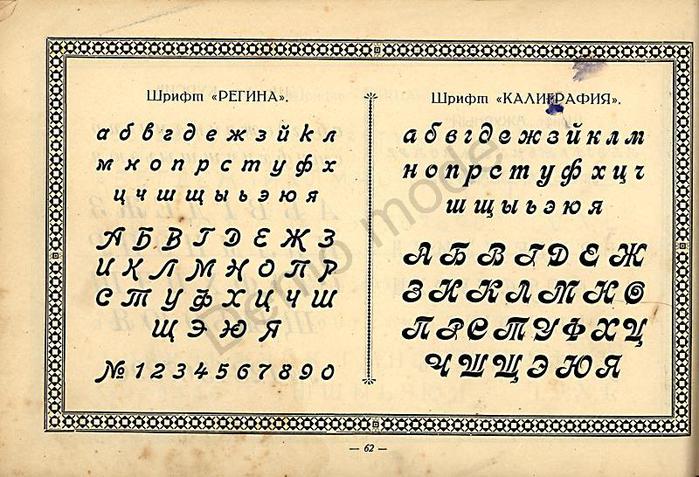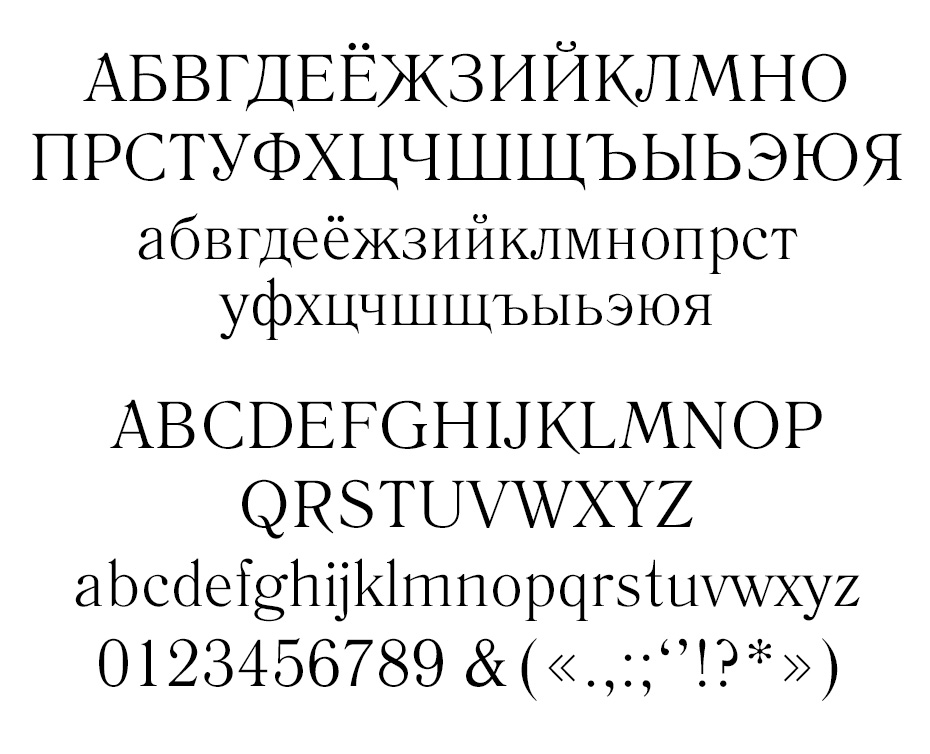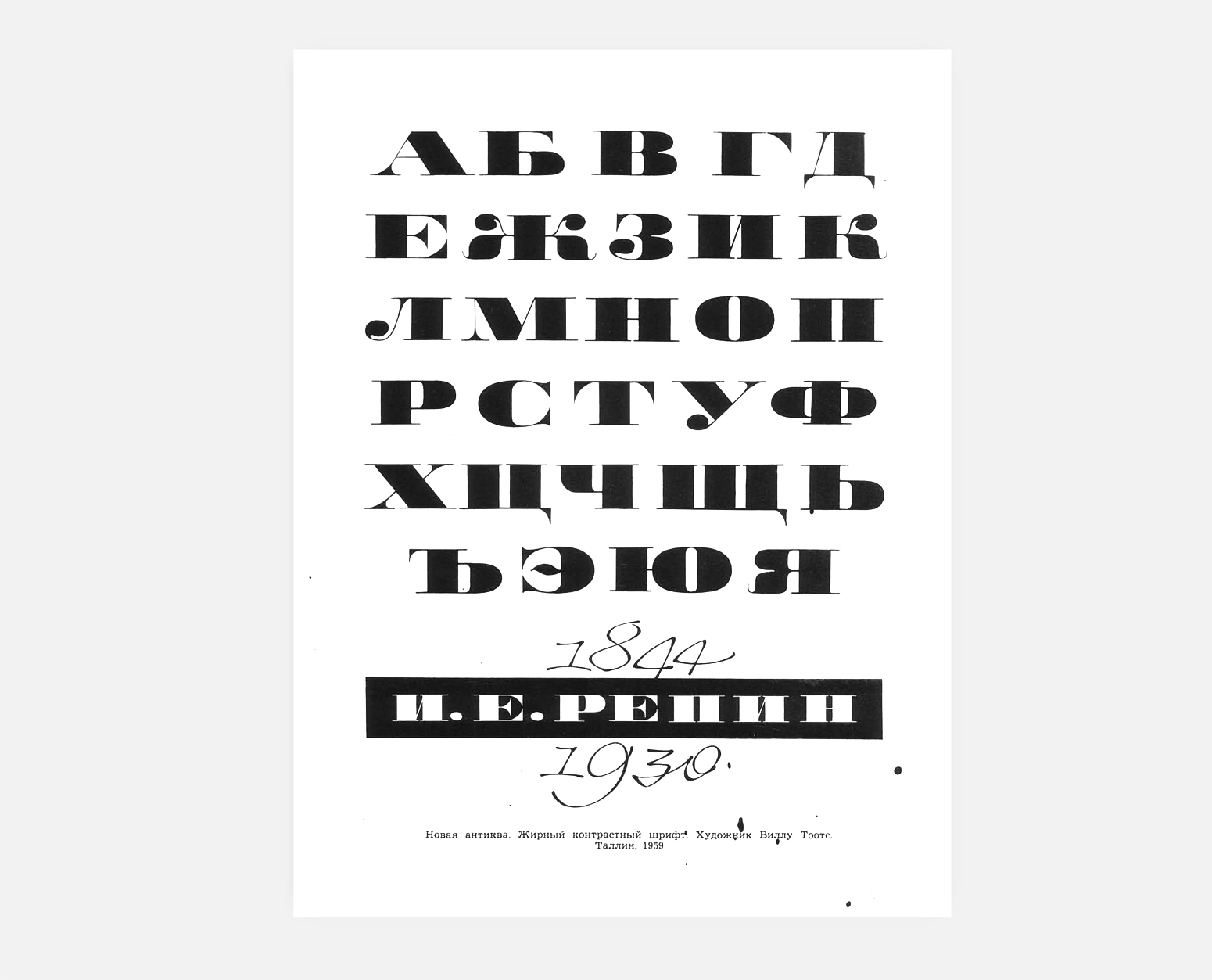
Классификация шрифтов. Вы сможете распознать характеристики… | by Виталий Шеянов
Главная «официальная» система классификации на сегодняшний день — система Vox-ATypI. Изначально составленная в 1954 году Максимильеном Воксом (Maxmilien Vox), в 1962 она была заимствована Международной Типографской Ассоциацией (Association Typographique Internationale — ATypI), которая внесла в нее небольшие поправки по включению в классификацию Гэльских шрифтов (семья шрифтов, разработанных для записи ирландского языка) как отдельной категории на конференции 2010 года. Согласно классификации Vox-ATypI, все шрифты разбиваются на 11 базовых категорий с дальнейшим делением внутри каждой отдельной категории. Отличный обзор этой классификации дает статья из Википедии.
Британские Стандарты Классификации Шрифтов, принятые в 1967 году, также основываются на классификации Вокса. По сравнению с последней они несколько упрощены и остаются неизменными с момента возникновения.
Роберт Брингхерст (Robert Bringhurst) в своей книге «Основы стиля в типографике», которая стала практически стандартом современной типографической литературы, группирует гарнитуры по категориям, близким к периодам в истории искусств — например, Барокко, Рококо, Романтизм и др.
Будучи дизайнером книг, Брингхерст фокусируется на текстовых гарнитурах и практически игнорирует выделительные шрифты.
В этой статье объединено несколько различных методик систематизации и показано то, что по меньшей мере в общих чертах принимается в качестве признанной системы классификации шрифтов (хотя разумеется всегда будут те, кто будет придерживаться какого-нибудь крайне необычного метода классификации, или те, кто будет отрицать целесообразность использования какого бы то ни было метода в принципе).
Итак следуя естественному историческому развитию шрифтов, в начале рассматриваются стили гарнитур с засечками.
Засечки — обычно перпендикулярный штрих, которым начинается и заканчивается буква. Будучи придуманными еще во времена римлян в монументальном шрифте, выгравированном на камне, засечка была естественным способом плавно свести штрих на нет, заодно придав его окончанию четкость. Отсюда их собирательное название антиква от лат. antiquus — древний.
Также первым печатным шрифтом был шрифт с засечками — края засечек почти касались друг друга в печатных изданиях, тем самым как бы объединяя буквы в единое слово.
Классический шрифт типографий предполагает использование засечек. Засечки бывают разных видов и стилей — прямоугольные, эллиптические, треугольные, овальные и так далее.
Гуманистическая/Венецианская антиква (Humanist/Venetian)
Гуманистическая/Венецианская антикваВ эпоху Возрождения, итальянские культурные центры такие как Флоренция и Венеция противопоставляли себя средневековью и возрождали античность, что нашло отражение в типографии. Вместо использования готического письма или фактуры, начиная примерно в 1465г книгопечатники стали создавать шрифты имитирующие латинский почерк философов того времени, однако этот почерк шел от каролингского письма VIII–IX вв, которое в ту эпоху ошибочно принималось за подлинное письмо античности. Тем не менее из-за своего происхождения данные шрифты называются гуманистическими или венецианскими в дань духу времени и географии Ренессанса.
Характерные черты: Гуманистические гарнитуры очень каллиграфичны, ярко выраженная наклонная ось овала наиболее заметная в строчной “o”, наклонная перекладина буквы “e”, что сближает с манерой рукописного письма правши.
Пропорции знаков довольно широкие, знаки разноширинные. Засечки чуть прогнутые. Соотношение величины сточных и прописных близко к золотому сечению. Как правило, данные шрифты с мелкой высотой строчных и малым контрастом между основными и соединительными штрихами.
Однако, не все гуманистические гарнитуры были придуманы в эпоху Возрождения многие из них были созданы в более позднее время, например, Centaur(1914) и Adobe Jenson (1996). Adobe Jenson, представленный на иллюстрации выше, основывается на работах книгопечатника эпохи Ренессанса Николя Жансона (Nicolas Jenson), выдающегося типографа, переехавшего из родной Франции в Венецию и внесшего значительный вклад в дело книгопечатания и проектирования шрифтов. Существуют также и гуманистические гротески, рассматриваемые далее. И хотя эра гуманистических гарнитур была важной вехой в истории шрифтов, это был относительно короткий период, послуживший толчком к развитию более современных форм начертания букв.
Примеры гуманистических гарнитур: Adobe Jenson, Guardi, Arno, ITC Berkeley, Stempel Schneidler
Гаральды, Итало-французская антиква старого стиля (Garaldes)
Гаральды, Итало-французская антиква старого стиляЧасть антиквы старого стиля, оказывается гораздо ближе к современным шрифтам, нежели гуманистические гарнитуры.
Термин «гаральд» — слово гибрид, составленное из имен двух выдающихся типографов периода конца XV середины XVI столетий, парижского словолитчика Клода Гарамона и венецианца типографа-издателя Альда Мануция. Изредка эту группу шрифтов называют «альдине» aldine по имени Мануция. Геральды охватывают исторический период до начала XVIII столетия, и шрифты, созданные в это время, демонстрируют удивительную живучесть.
Характерные черты: Менее каллиграфичны, так как печатные шрифты постепенно перестают рассматриваться имитацией рукописного текста. Оси овалов стремятся к перпендикуляру хотя еще и остаются под острым углом к линии шрифта. Значимое отличие от гуманистических шрифтов перекладина строчной «e» становится параллельный линии шрифта. Засечки более длинные и острые, а символы более пропорциональные. Возрастают различия между основными и соединительными штрихами по всей вероятности благодаря развитию технологий печати.